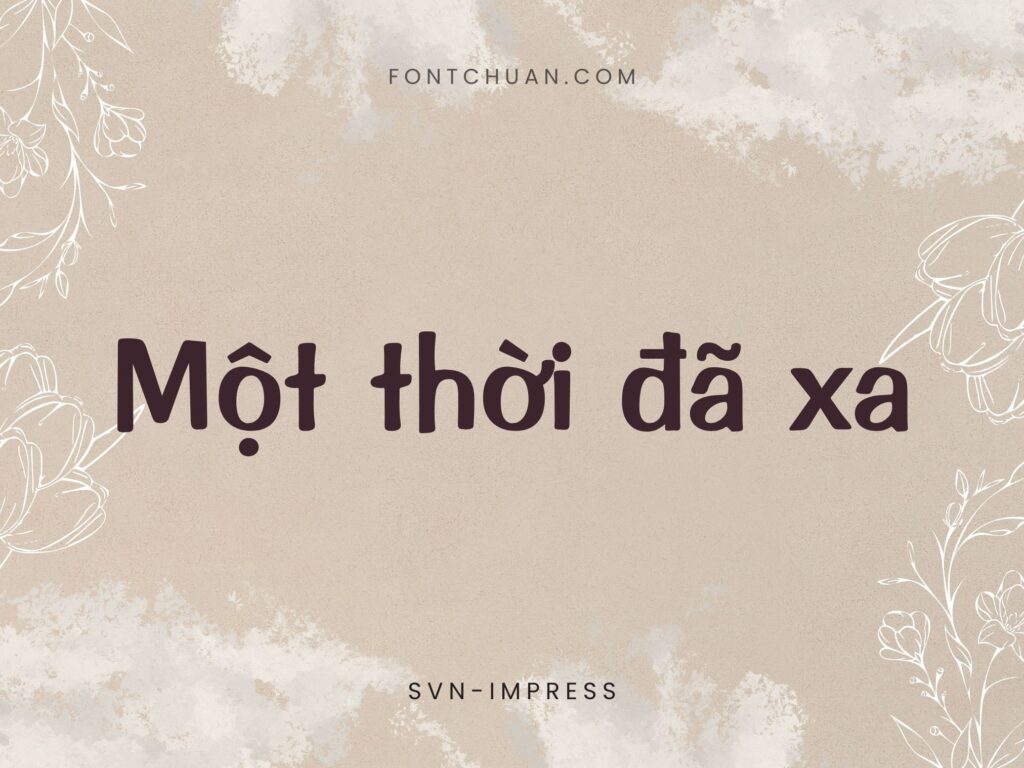
Font SVN Impress Việt Hóa
Tác giả Font: Bitsream
Font SVN Impress là phiên bản Việt hóa của kiểu chữ Impress, được thực hiện bởi STYLEno.1 Fonts. Impress là một kiểu chữ hiển thị (display) với thiết kế độc đáo, mang phong cách vui nhộn và thân thiện. Các ký tự được thiết kế với đường nét mềm mại và hơi hướng hoạt hình, tạo cảm giác gần gũi và hấp dẫn. Font này bao gồm các ký tự chữ hoa, chữ số và dấu câu, hỗ trợ đa ngôn ngữ. Với thiết kế đặc trưng, Impress phù hợp cho nhiều mục đích sử dụng như thiết kế tiêu đề, logo, poster, bao bì sản phẩm và các ấn phẩm truyền thông.
SVN Impress lý tưởng cho các dự án thiết kế yêu cầu sự vui nhộn và thân thiện, như thiết kế tiêu đề, logo thương hiệu và các ấn phẩm truyền thông. Các ngành nghề như giáo dục, quảng cáo và ẩm thực có thể tận dụng font này để tạo điểm nhấn trong thiết kế. Ngoài ra, font cũng thích hợp cho các sự kiện như Sinh nhật, Tết, Giáng sinh và các lễ hội khác.